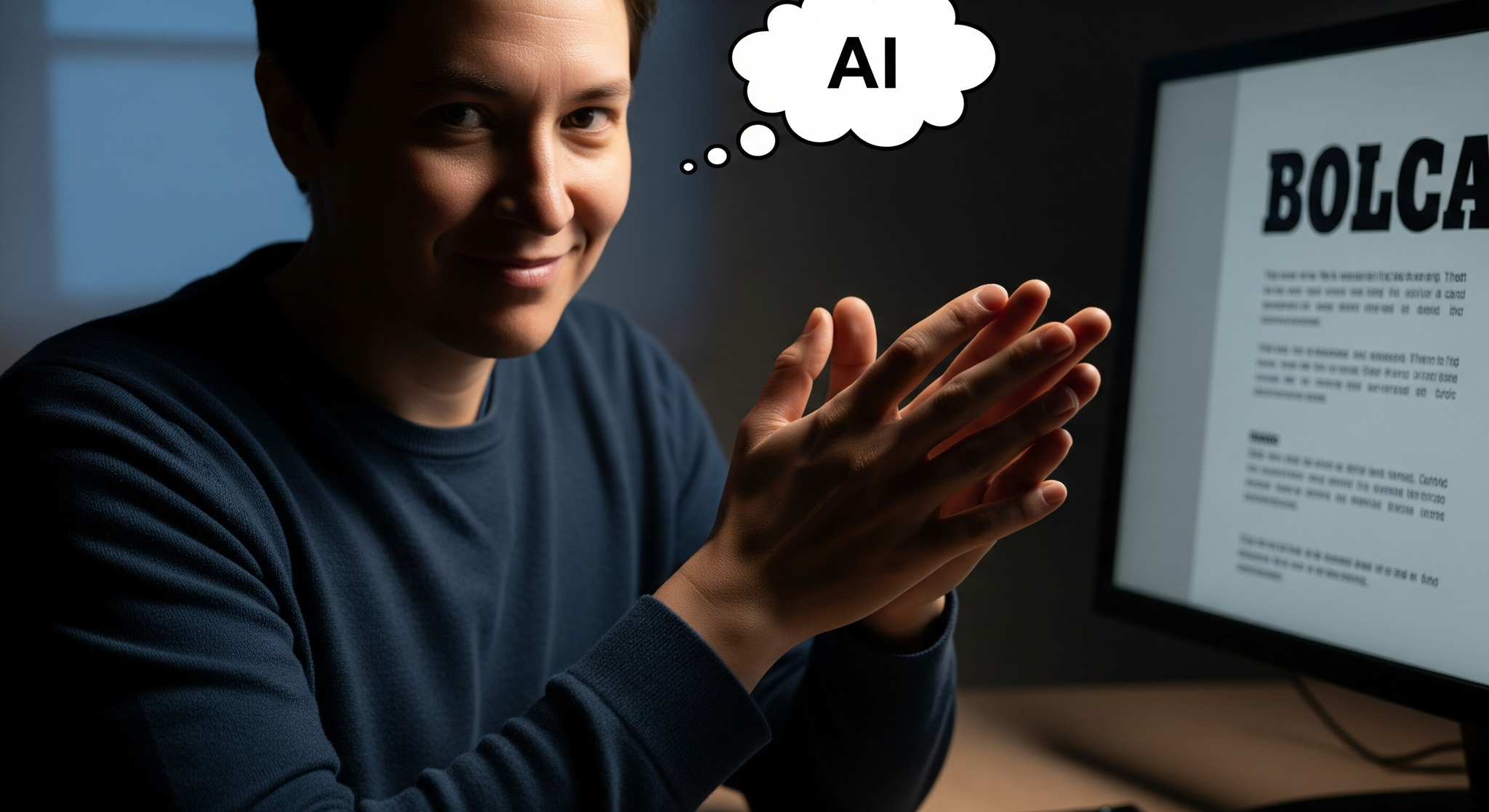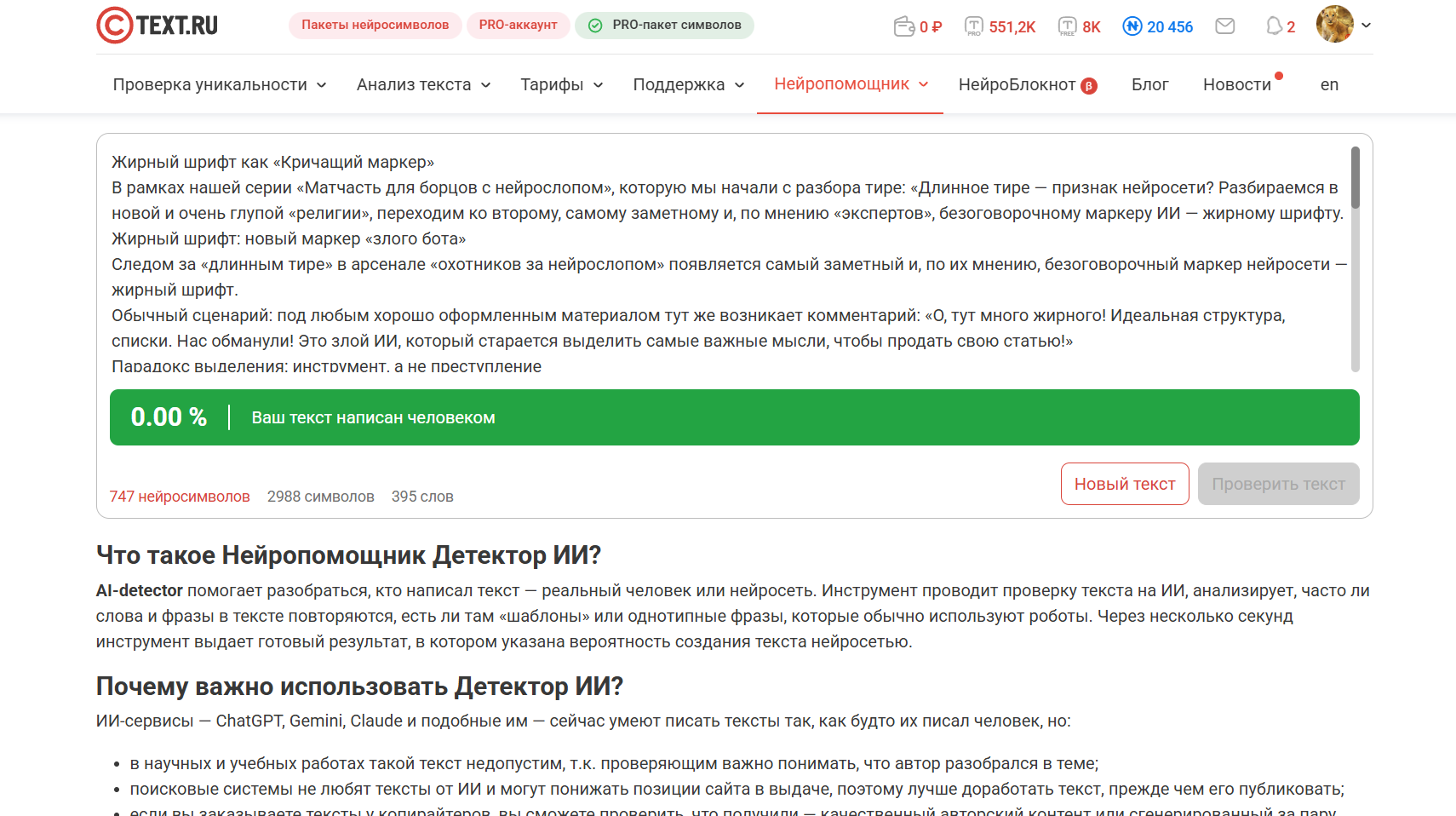
Жирный шрифт как «Кричащий маркер»
В рамках нашей серии «Матчасть для борцов с нейрослопом», которую мы начали с разбора тире: «Длинное тире — признак нейросети? Разбираемся в новой и очень глупой «религии», переходим ко второму, самому заметному и, по мнению «экспертов», безоговорочному маркеру ИИ — жирному шрифту.
Жирный шрифт: новый маркер «злого бота»
Следом за «длинным тире» в арсенале «охотников за нейрослопом» появляется самый заметный и, по их мнению, безоговорочный маркер нейросети — жирный шрифт.
Обычный сценарий: под любым хорошо оформленным материалом тут же возникает комментарий: «О, тут много жирного! Идеальная структура, списки. Нас обманули! Это злой ИИ, который старается выделить самые важные мысли, чтобы продать свою статью!»
Парадокс выделения: инструмент, а не преступление
Вся ирония ситуации в том, что жирный шрифт — это не «клеймо искусственного интеллекта», а базовый, незаменимый инструмент редактуры. Его использование демонстрирует заботу о читателе, является основой структурирования текста и визуальной иерархии! Уберите его — и перед вами останется сплошная, нечитаемая «простыня», которую не осилит даже самый мотивированный читатель.
Forbes как учебник: Правила профессиональной редактуры, где жирный шрифт — это не «признак ИИ», а четкий стандарт выделения ключевых тезисов.
Жирный шрифт — это признак профессионального оформления, а не работы ИИ.
Специально для «экспертов по нейрослопу»! Откройте любую серьезную статью на Forbes, vc.ru или даже научную монографию. Что вы увидите? Ключевые тезисы, определения и важные части текста, выделенные... именно, жирным. Если следовать этой логике, то все академики, журналисты и редакторы, работавшие над этими текстами, — это массовая нейросеть.
Визуальная иерархия в действии. Профессиональная редактура всегда использует выделение для того, чтобы сделать текст понятным и легко воспринимаемым.
Откуда растут «ноги» стереотипа: почему ИИ так любит Bold
Как и в ситуации с тире, стереотип возник из-за особенностей обучения моделей. Нейросети действительно активно используют выделение, потому что они тренировались на массивах эталонного, высококачественного контента.
В идеальной модели текста, которую усвоил ИИ:
Каждая важная мысль должна быть визуально акцентирована.
Структура текста должна быть максимально четкой для быстрого считывания информации.
Ключевые выводы или анонсы всегда выделяются для немедленного привлечения внимания.
В отличие от человека, который может торопиться, забыть или полениться отформатировать текст, ИИ неуклонно следует идеалу читабельности. И эта сверхъестественная структурность и аккуратность теперь воспринимается как подозрительный фактор.
Итог: Ловушка идеального текста
Мы приходим к абсурдному шаблону, который стал новым догматом в сети:
Текст идеально структурирован, грамотен, ключевые мысли выделены? — Автоматически ИИ.
Текст сбивчив, нелогичен, изобилует ошибками и не имеет выделений? — Настоящий, неидеальный, живой Человек!
Этот нелепый фильтр автоматически делает подозрительным любой качественный материал. Если вы приложили усилия, чтобы сделать свой текст понятным и легко воспринимаемым, готовьтесь услышать вердикт: «Ваша нейросеть пишет лучше, чем вы!»
Вместо P.S. (Аргумент, который не работает)
Заключение ведущего детектора: 100% человек. Увы, для «борцов с нейрослопом» этот аргумент не работает.
Для демонстрации абсурда. Мы прогнали и этот текст через один из самых популярных платных «детекторов ИИ». Результат — 100% человек. Все эти «преступные» тире, жирный шрифт и идеальная структура написаны живым автором. Однако, как показывает практика, заключение «100% Человек» от ведущего сервиса не стоит ничего против коллективного «внутреннего убеждения»: «Всё равно видим признаки ИИ». Это и есть подлинная классика жанра «борьбы с нейрослопом».